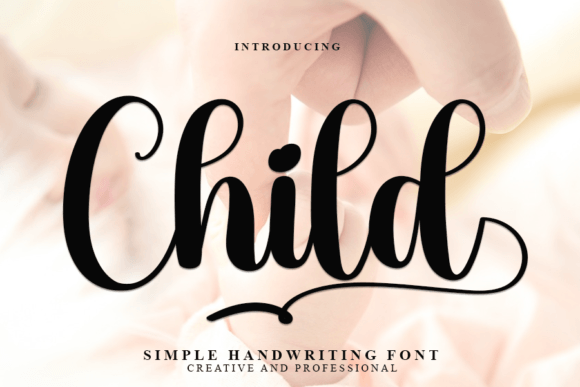
Child
Child – La police manuscrite qui séduit par sa délicatesse
Vous cherchez une police d’écriture qui allie élégance et originalité ? Child est la réponse à vos attentes. Conçue avec un souci du détail remarquable, cette police manuscrite apporte une touche cool et unique à tous vos projets créatifs.
Pourquoi choisir la police Child ?
- Design délicat : chaque caractère est tracé à la main, offrant une sensation authentique et chaleureuse.
- Polyvalence : idéale pour les lettres, invitations, emballages alimentaires, titres et bien plus encore.
- Lisibilité optimale : même avec son style manuscrit, la police reste claire et facile à lire.
- Impact visuel : grâce à son aspect « cool », elle capte immédiatement l’attention de votre audience.
Utilisations concrètes de Child
Que vous soyez graphiste, organisateur d’événements ou propriétaire d’une petite entreprise, Child s’adapte à tous les contextes :
- Cartes d’invitation personnalisées pour mariages ou anniversaires.
- Étiquettes et emballages de produits alimentaires artisanaux.
- En-têtes et titres de newsletters ou de blogs pour un rendu plus humain.
- Affiches promotionnelles ou flyers qui se démarquent en rayon.
- Création de logos à l’allure manuscrite pour une identité de marque unique.
Conclusion – Un must‑have pour vos projets créatifs
En résumé, Child est bien plus qu’une simple police manuscrite ; c’est une véritable invitation à exprimer votre créativité avec finesse et modernité. Son style délicat, sa grande polyvalence et son impact visuel en font le choix idéal pour tous ceux qui souhaitent donner du caractère à leurs créations. N’attendez plus, téléchargez Child dès aujourd’hui et laissez votre imagination prendre le dessus !